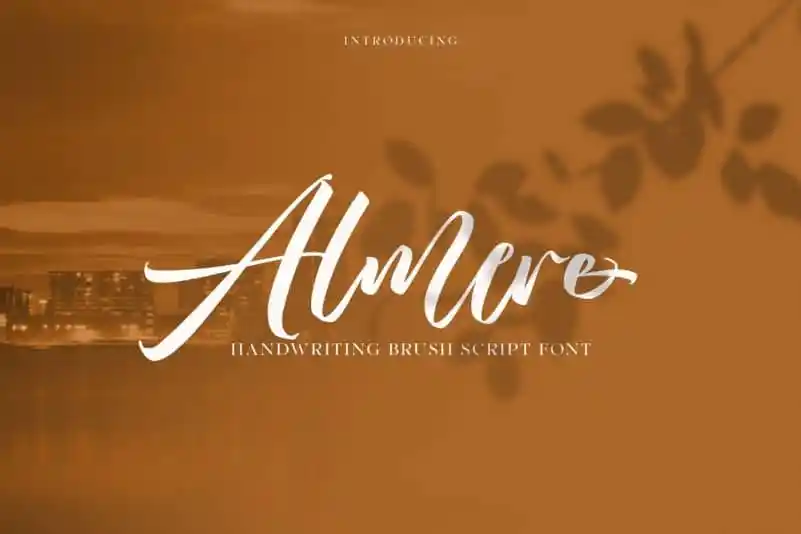
Almere Script Font – Download Grátis
A Almere Script Font é uma escolha perfeita para aqueles que procuram uma fonte script bold com estilo forte e masculino. Ela inclui ligaturas únicas e alternativas, criando um visual atraente e interessante. O designer joelmaker inspirou-se em um caderno de bilhete manual para criar esta fonte, utilizando canetas-pen e arrumando as letras cuidadosamente para produzir uma fórmula de script com forma semelhante à escrita oriental moderna, única, suave e limpa. A Almere Script Font é perfeita tanto para o design de letrinhas grandes quanto para a criação de logotipos e outras formas visuais que necessitam de um estilo único.